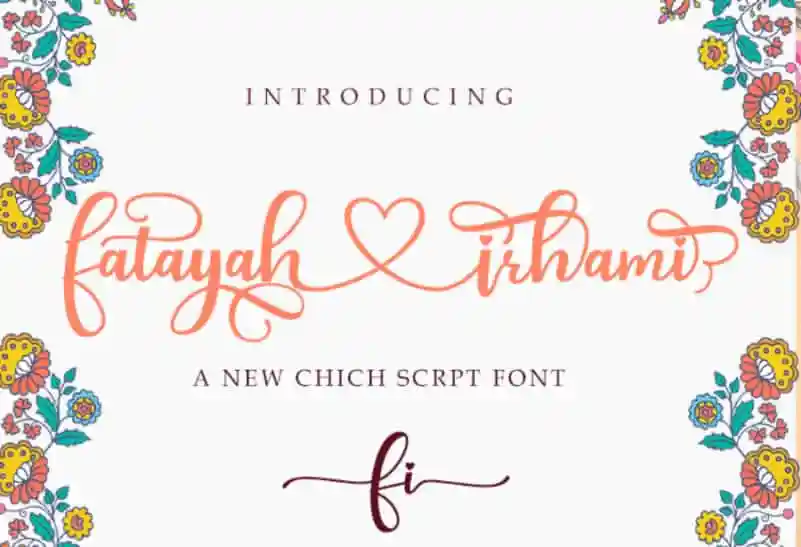
Fatayah Irhami Script Font – Download Grátis
A Fatayah Irhami Script Font é uma grife de alta qualidade que traz alegria e elegância à sua designação. Com seu estilo delicado e suave, ela se destaca para qualquer aplicação que necessite de um toque autêntico do papel da mão humana. Perfeita para anúncios de casamento, cartões de agradecimento, citações, cartões de felicitação, logotipos e até mesmo as identidades corporativas, a Fatayah Irhami Script é um verdadeiro complemento ao seu trabalho. Além disso, sua PUA encoded permite que você acessa todos os caracteres e espelhos com facilidade. A fonte destaca-se por ter uma linha de fundo variável, linhas suaves, belos desenhos e alternativas surpreendentemente estonteantes. Sua versatilidade é limitada apenas pelo seu potencial incrível.